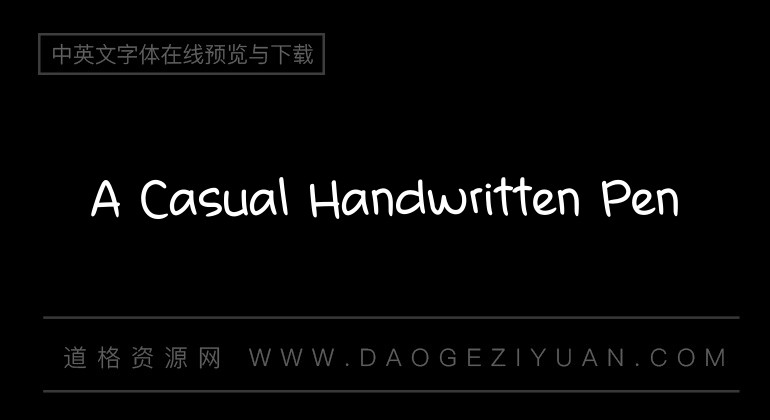
A Casual Handwritten Pen 字体是一款潇洒自然的手写字体,它具有温暖的氛围和活泼的表现形式,适合用于各种友好的环境,如婚礼、婚庆、节日等。它的字形有着自然的流动感,每个字母都有自己独特的形状,使得它看起来有着温暖的气氛。它的字体大小也可以根据需要进行调整,以满足不同的设计需求。内容介绍
A Casual Handwritten Pen是一款非常不错的手写艺术字体,具有很好的视觉感,适合于文化类的宣传设计、商业类品牌的广告和产品包装设计以及个性化文字排版等较多场景。